有什么能像文字改变整个设计和文档的意义一样简单的吗?当然,那就是字体还能强调或者添加你传达文字的意义。
文字编辑可以帮助您与用户产生连接,树立品牌,并确立整个项目的基调。错误的字体可以使设计感持平,脱节,甚至会使用户对你的品牌产生错误的印象。现在,让我们通过结合以下的一些实例,来告诉你一些关于字体运用的小知识吧。
搭配氛围和信息
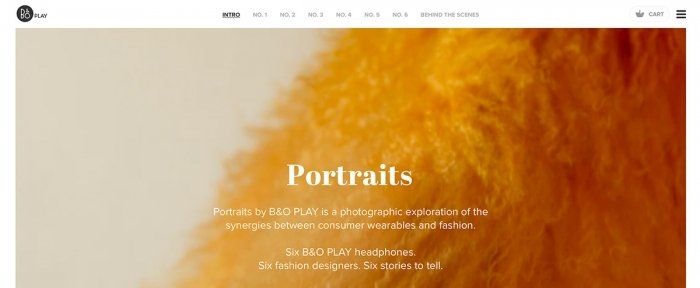
这个说法听起来有点疯狂,但在它确实是这样的:每一个字体都代表一种氛围。就像你有自己的情绪一样,它可以根据不同的环境变得十分微妙。
这种氛围有助于建立项目中的上下文。它决定了人们如何感受和思考的内容,连接了用户行为,决定了你是谁和用户会怎么样回复你。 (码字的压力太大了,对吧?)当你开始构建一个项目的时候,想清楚你的项目想要传达什么,该如何正确的建立沟通,以及不同风格的氛围是如何建立的。
区别信息
你要传达的意思是:
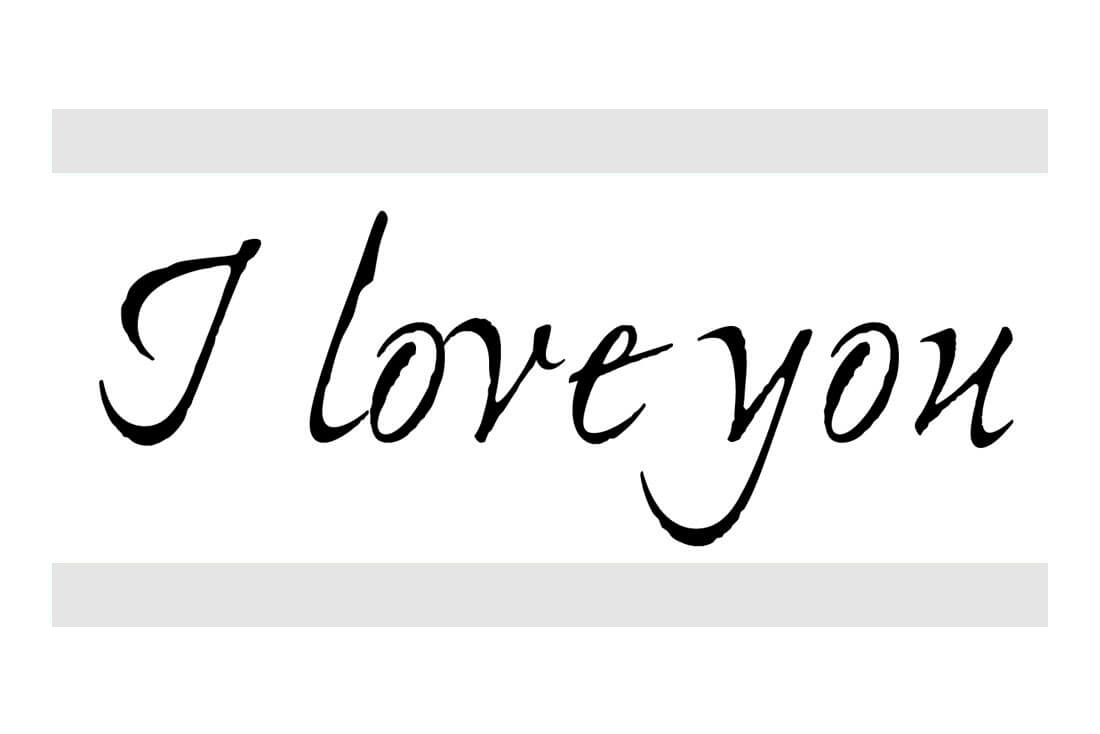
还是你尝试这样说:
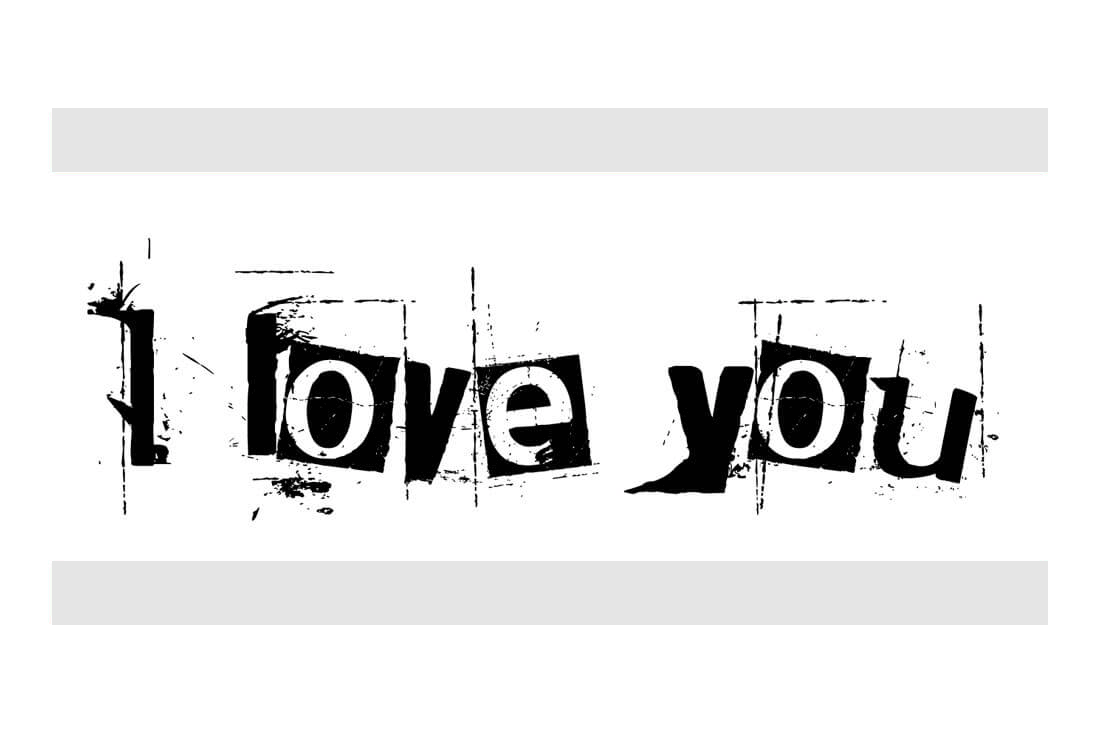
唯一不同的只有字体,看出两者之间的区别了吗?
字体个性搭配
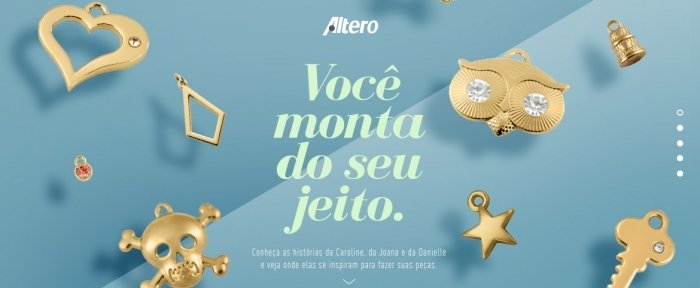
并没有确切的标准说明何种字体具有何种个性,但是事实上,很多时候,你在看到文本和承载文本的字体的时候,直观上会觉得它们仿佛是带着一定语气告诉你的。(如果不相信,你可以回头看看前面的例子)
以下有一些各种字体所代表的不同个性指南,可以用作各种不同的排版风格。
- Serif: 永恒,经典
- Modern serif: 有魅力,时尚
- Slab serif: 重要,引人注目
- Sans serif: 中性,简约
- Ultra thin or condensed: 权威,快速
- Italic (serif or sans serif): 运动,独特
- Black or bold (serif or sans serif): 重要,静止
- Script: 优雅,个性
- Novelty: 休闲,灯火阑珊
- Geometric:复古,童趣
- Monospaced: 代码,技术感
- Bubble or rounded:友善,快活
- Vintage: 新潮,酷
- Grunge: 粗犷,神秘
避免陈词滥调
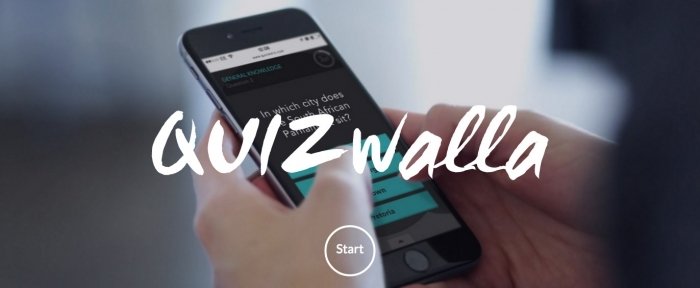
这是最困难的部分:不要因为一追求大众或者因为不确定要怎么做,就陷入一种陈词滥调的排版方式。去网上搜索不同的项目列表需要用什么字体,该注意什么,这样你就不会陷在里面了。
搭配文本和字体是一个不断磨合的过程,也是一种模糊的艺术,但是你需要知道,这个过程是必经之路。
你可能偏爱用有趣的内容和serif风格的字体搭配使用,或者用一种更男性化的Script字体。正如这种字体配对原则,选择一种字体展示,大写字母,并通过其他元素补充强调文本。这种搭配可能是传统的serif和 sans serif字体,或者其他现代与复古的结合。
考虑背景
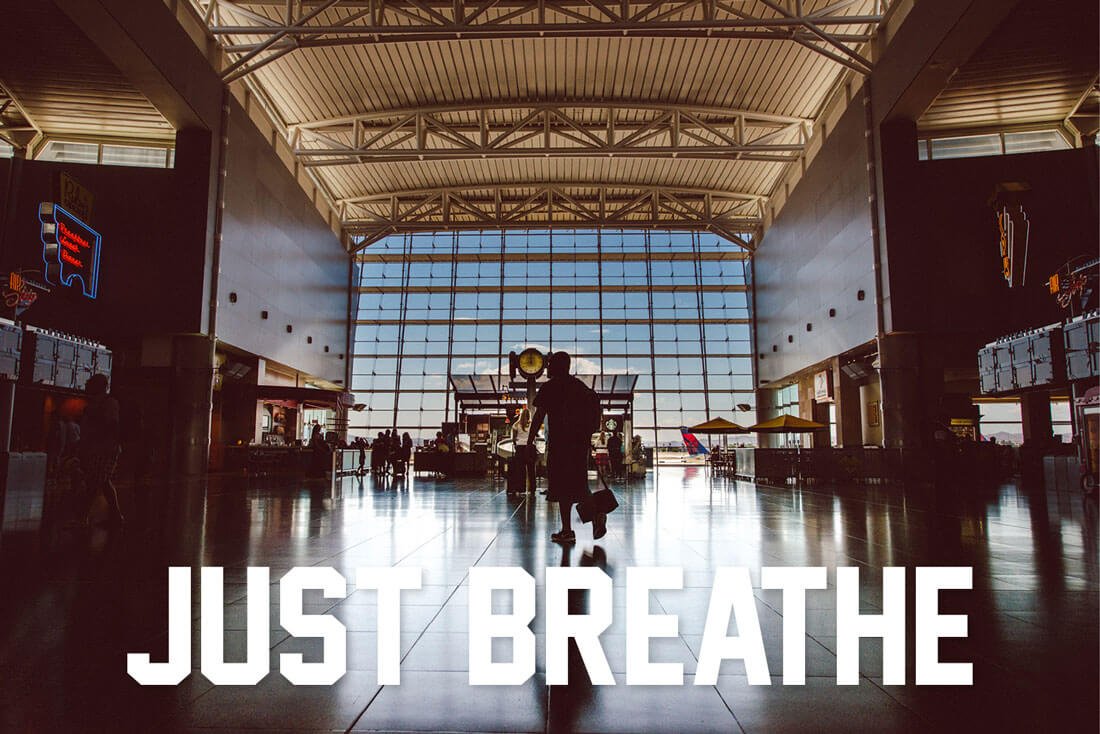
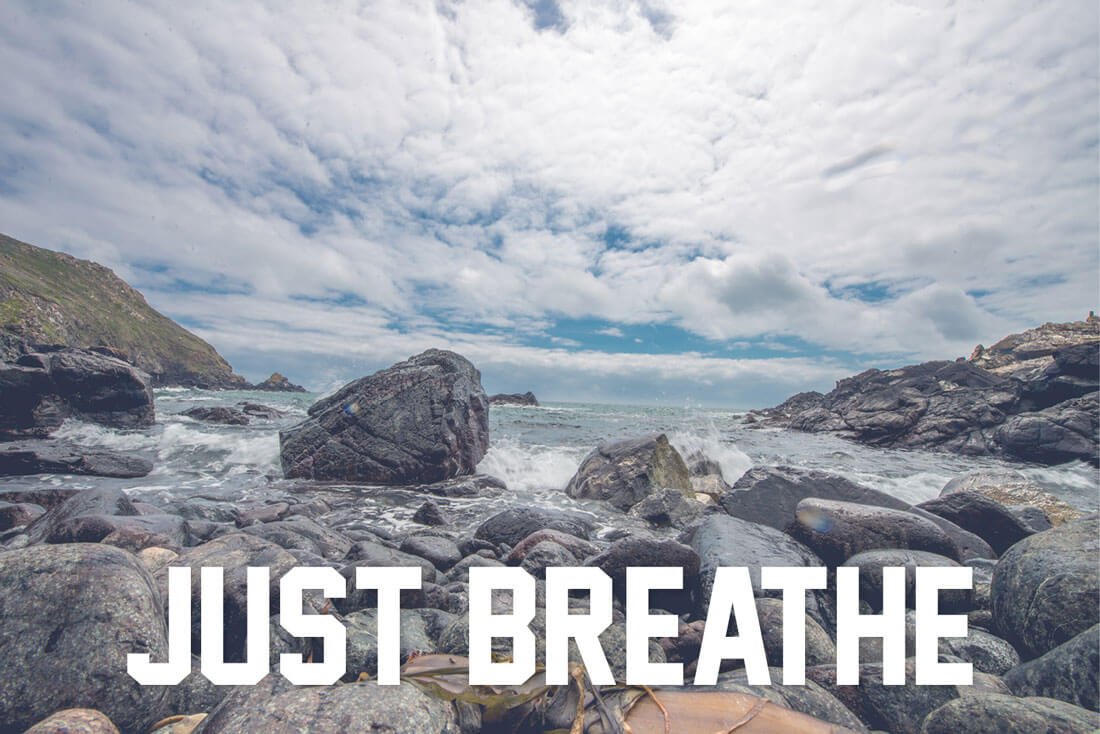
如何进行字体排版设计的一个重要因素就是,文本周围的其他元素。这些元素可以使图上的任何东西,颜色,线条或者其他背景。不同的组合可以让受众有不同的感受。
想象一下简单的sans serif字体。这种字体一般都比较中性,能在各种背景中也占有一席之地。以上述的两个图像为例,你觉得两者有何区别吗?两个图片中的文本字体都是一样的,但是所产生的效果有很大的不同。在机场那张你可能会感受到匆忙和焦急,但在海边的岩石上,你能感受到的是心情的平静。
站在受众角度感受
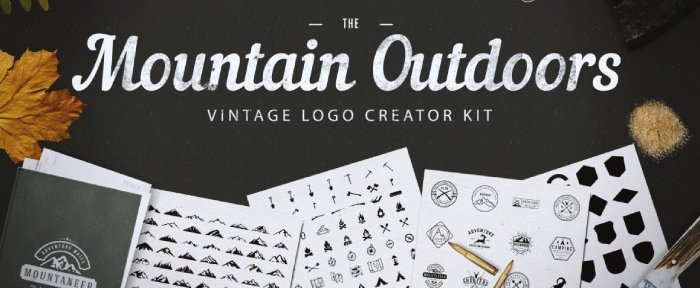
当涉及到排版和氛围的问题时,还有一个你无法控制的因素,那就是对于你的文本和字体排版,你的目标受众是怎么看的。
就拿Comic Sans字体为例,这个字体本身就非常可爱,但是大部分设计师不会选择它。如果某个设计师在项目中使用这种字体,那么他的同行会笑他傻。但事实上,Comic Sans字体是一种非常流行的字样,教会公报,业余通讯,简单的标牌等等,你到处都可能会看到。
在这里你可能会发现这样一个问题,人各有异,对字体的感受也各不相同。
用户会从很多不同角度的设计。首先考虑你的读者,试图预测他们对设计有什么评价和感受。他们将如何看待您的排版选择?你可以更多的站在他们的角度上进行思考。
虽然你不会每次都找到一个完美的解决方案,但站在受众角度思考是一个非常实用的方法。
五种小白尽量少用的字体
鉴于许多时候,我们只会浮光掠影的一扫而过,如果字体很糟糕,那么一个非常好的设计就可能被一个非常愚蠢的的字体选择给毁了,还有一种情况就是字体的过度使用或者误用,同样会毁了一个好创意。开个玩笑,这里的五种字体,初入门的小白轻易还是不要尝试了。
- Papyrus:这种字体很难搭配任何设计,并且可读性较差。
- Jokerman:任何版本的这种字体都有波点,尖刺,而且任何妄图在短时间内传递所以信息这种想法都是非常荒唐的。
- Times New Roman:文字处理器和英语试卷的默认字体。作为一个字体来讲,普通实用,但有可能会让用户觉得设计师有点懒惰哦。
- Impact:如果你想对用户大喊:“这是非常重要的信息!你必须现在就读他!”那你就用吧。(这是一个相当不错的字体。。。。直到memes毁了它)
- Comic Sans: 这个说的够多了。
结论
你的心情,你的观众的情绪和版式的情绪都结合起来,创造一个项目的整体感觉。它不仅仅是一种文字信息,文字本身的形式也是非常重要的。
规划项目时记住一点,努力调动目标观众对设计作品的情绪,并在使用清晰适当的排版,使用可读的传播文本。如果你前进的道路上遇到挫折,不用担心- 从这些错误中学习,在下一个项目重新思考,重新探索。